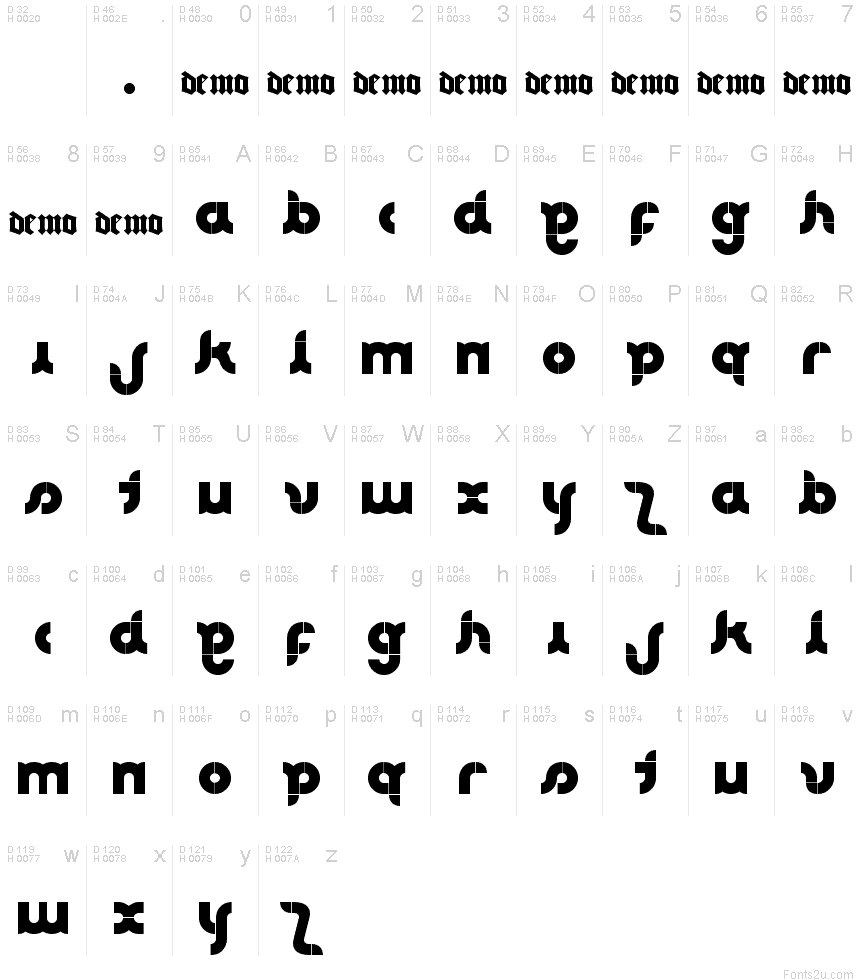
Die Schrift CLUB von Marcio Hirosse (Fabrika de Typos) besticht durch ihren kompakten, abgerundeten Look, der verspielt wirkt und einen Hauch von Lounge-Atmosphäre versprüht. Die eng gesetzten Formen verschmelzen zu einem markanten Rhythmus. Diese kostenlose Schriftart setzt auf eine dekorative Retro-Sans-Ästhetik, wodurch kurze Wörter kräftig, geschmeidig und sofort einprägsam wirken.
CLUB eignet sich besonders gut für Poster, Logo-Entwürfe, Album-Art, Sticker, Party-Flyer, Verpackungen, Social-Media-Grafiken und Überschriften, bei denen Wärme wichtiger ist als strikte Lesbarkeit. Diese kostenlose Schrift hat genug Persönlichkeit, um ein Layout allein zu tragen, und lässt sich am besten mit einer schlichten, neutralen Sans für kleinere Begleittexte kombinieren.